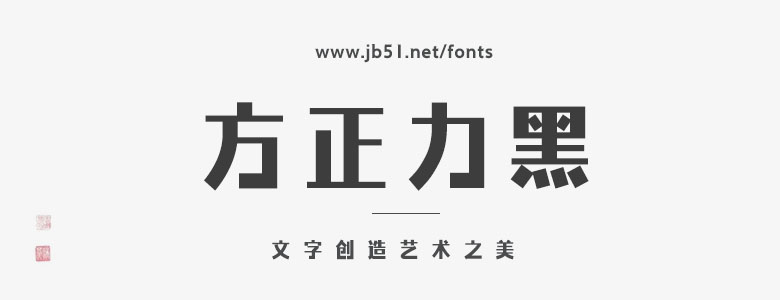
力黑字形整體外形豎長(zhǎng),摒棄了正方形的呆板,注入現(xiàn)代時(shí)尚基因,更傾向于滿足現(xiàn)代橫排的版式需求。筆畫基礎(chǔ)部件為大塊面的幾何造型,猶如用大排刷書寫而成,充滿了力量感,橫細(xì)豎粗,借鑒了宋體字的特征來注入優(yōu)雅基因,同時(shí)沖淡粗筆畫帶來的壓迫感,為字體的多元化應(yīng)用提供了可能,在某些筆畫部件的交接處刻意做了斷開處理,強(qiáng)調(diào)字體的書寫性和親近感,粗體力發(fā)千鈞,細(xì)體精細(xì)雅致且具備很好的延展可能。適用于時(shí)尚、運(yùn)動(dòng)、汽車、工業(yè)、建筑、藝術(shù)、娛樂等領(lǐng)域的廣告、包裝、品牌、出版物等應(yīng)用環(huán)境。